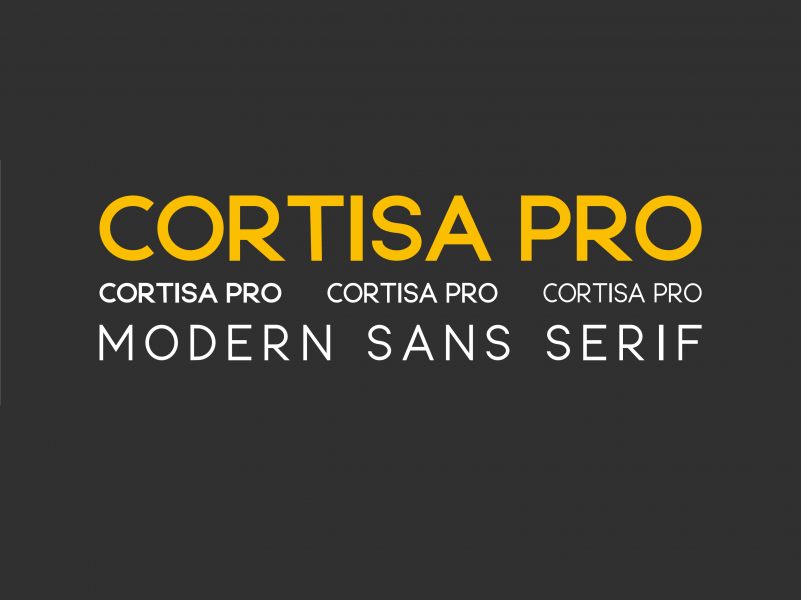
Cortisa Pro Font – Download Grátis
Esta fonte é uma tipografia sans serif condensada que surge como a escolha perfeita para designers experimentados e novatos. Seu estilo moderno e confiante, idealmente projetado para headlines, logotipos, embalagens, materiais de mídia impressa e muito mais, traz consigo uma atmosfera vintage industrial sem perder sua versatilidade. Cortisa Pro é a fonte perfeita para quem procura um look moderno que ainda consegue transmitir uma sensação nostálgica do passado. Seu desenho elegante e forte o tornam uma opção ótima não apenas para projetos visuais, mas também para elementos gráficos em filmes, seções de notícias em revistas ou materiais de identidade visual criativos. A sintaxe do Cortisa Pro permite que você personalize sua criação, independentemente da funcionalidade específica a ser usada. Seja uma marca que precisa ser rápida e direta, um logotipo que precisa ser atraente, ou até mesmo um design editorial em revistas de moda, o Cortisa Pro estará sempre ao seu lado. É perfeito para criar um visual único, marcante e moderno, sem perder sua originalidade e simplicidade elegante. Esta fonte é uma opção confiável para qualquer projeto que exija qualidade e consistência de design. Com uma aparência atraente e resistente aos detalhes, pode ser usada tanto em trabalhos profissionais quanto em projetos pessoais. E com seu poderoso conjunto de caracteres e sua capacidade de personalização, o Cortisa Pro é um ativo valioso para qualquer criador de conteúdo visual.